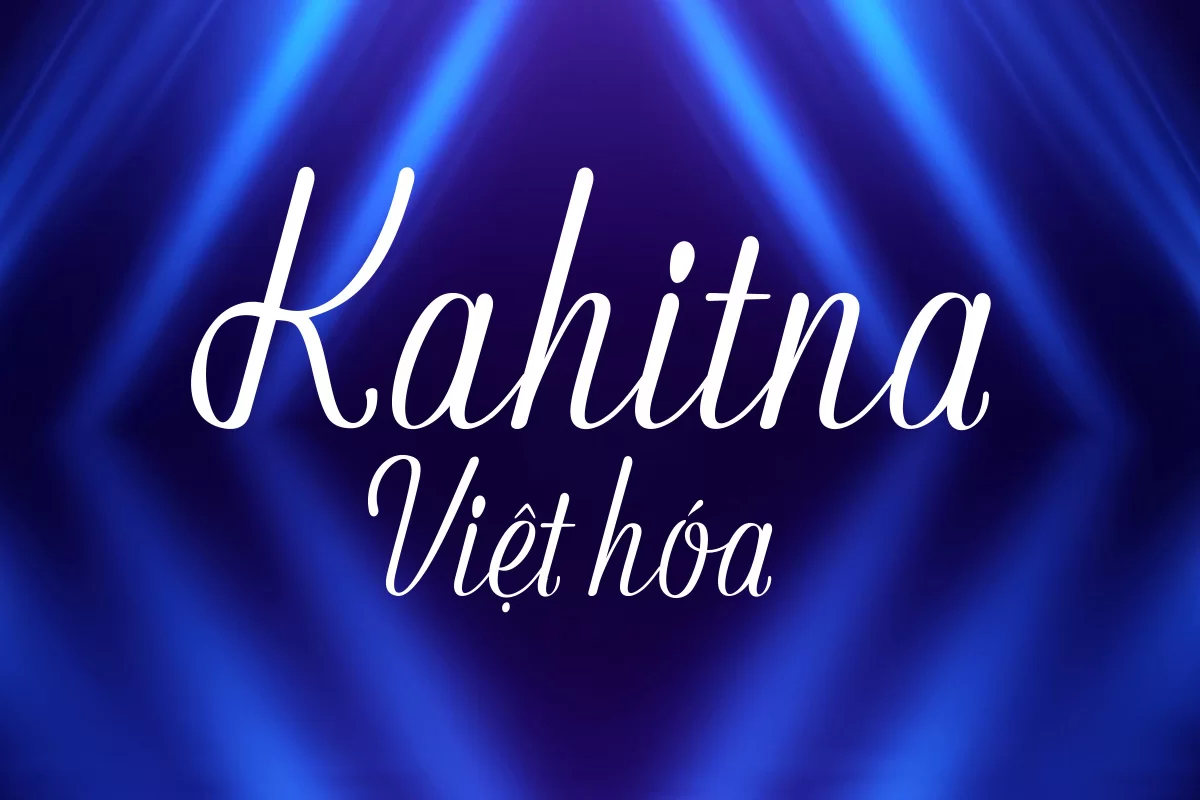
Kahitna Việt hóa là font chữ Script thanh mảnh với những nét bút mềm mại, uyển chuyển, mang đến cảm giác tinh tế và duyên dáng. Các đường nét đều đặn, độ nghiêng nhẹ tạo sự bay bổng, phù hợp cho thiết kế thiệp mời, logo thương hiệu, trích dẫn nghệ thuật hay các ấn phẩm cần sự sang trọng và nữ tính. Phiên bản Việt hóa hỗ trợ đầy đủ dấu tiếng Việt, giúp bạn dễ dàng sử dụng trong các dự án sáng tạo mà vẫn giữ trọn vẻ đẹp nguyên bản.